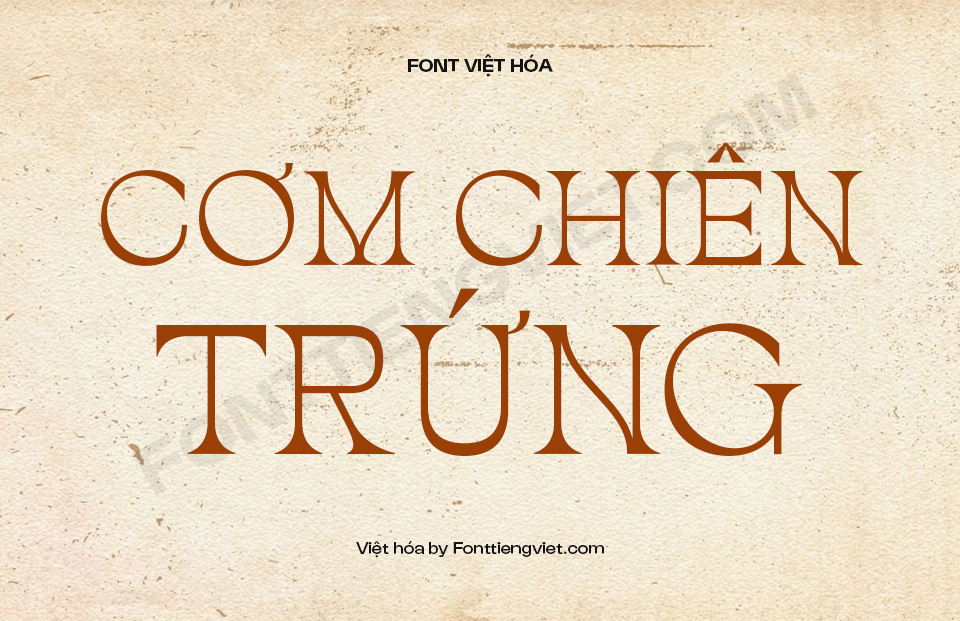
Font Việt hóa 1FTV VIP Maorin
Trong thế giới sáng tạo, việc lựa chọn một bộ Font Việt hóa 1FTV VIP Maorin chất lượng đóng vai trò quan trọng giúp nâng tầm giá trị cho mọi tác phẩm nghệ thuật. Đây là một bộ Font Miễn Phí được tinh chỉnh kỹ lưỡng về mặt hiển thị, giúp người dùng dễ dàng truyền tải thông điệp một cách ấn tượng. Với đường nét thanh thoát nhưng không kém phần mạnh mẽ, Maorin đã trở thành lựa chọn ưu tiên của cộng đồng thiết kế tại Việt Nam khi tìm kiếm sự khác biệt trong phong cách trình bày văn bản.
Đặc điểm nổi bật của Font Việt hóa 1FTV VIP Maorin
Thiết kế hiện đại và linh hoạt
Bộ Font Việt hóa 1FTV VIP Maorin sở hữu cấu trúc ký tự cân đối, mang lại cảm giác dễ nhìn và chuyên nghiệp trên nhiều nền tảng khác nhau. Điểm mạnh lớn nhất của bộ font này chính là khả năng hiển thị tiếng Việt hoàn hảo, không bị lỗi dấu hay sai lệch khoảng cách giữa các con chữ. Điều này cực kỳ hữu ích cho các bạn học sinh và giáo viên khi soạn thảo giáo án hoặc làm báo cáo thuyết trình sinh động hơn.
Ứng dụng đa dạng trong thực tế
Người dùng có thể ứng dụng bộ font này vào việc thiết kế bìa sách, làm tiêu đề video hoặc tạo ra những tấm thiệp chúc mừng đầy ý nghĩa. Sự kết hợp giữa nét cổ điển và hơi thở hiện đại giúp cho mỗi bản thiết kế đều mang một dấu ấn cá nhân đậm nét, thu hút ánh nhìn ngay từ giây đầu tiên.
Hướng dẫn sử dụng và kết luận
Để tận dụng tối đa vẻ đẹp của bộ chữ, bạn nên kết hợp nó với các tông màu trung tính để tạo sự tương phản rõ rệt. Việc sở hữu một công cụ mạnh mẽ như thế này sẽ giúp bạn tiết kiệm thời gian mà vẫn đảm bảo tính thẩm mỹ cao nhất. Hy vọng rằng mẫu Font Miễn Phí, Font Việt Hóa, Font Việt hóa 1FTV VIP Maorin sẽ là người bạn đồng hành đáng tin cậy trong hành trình sáng tạo sắp tới của bạn.